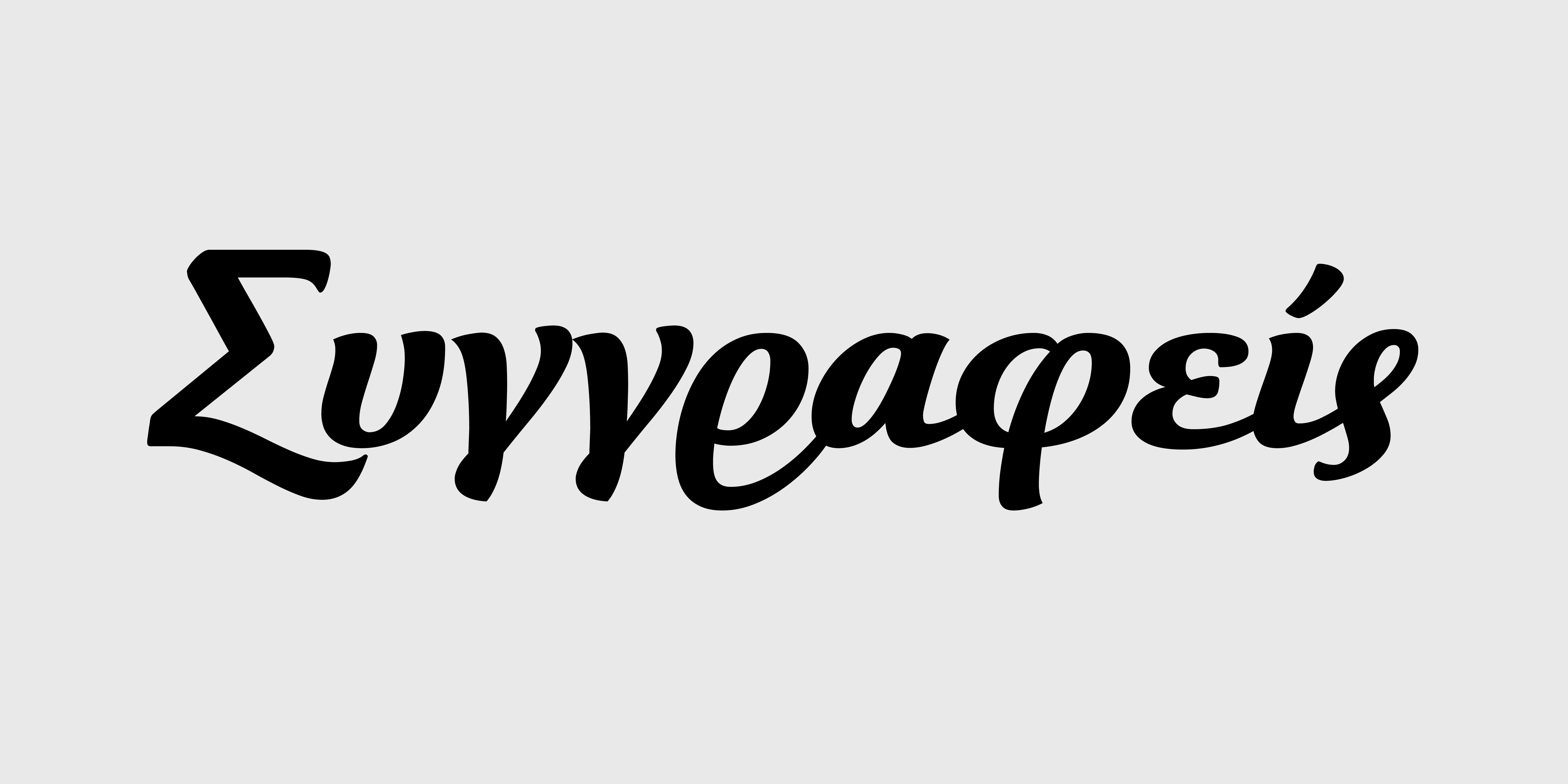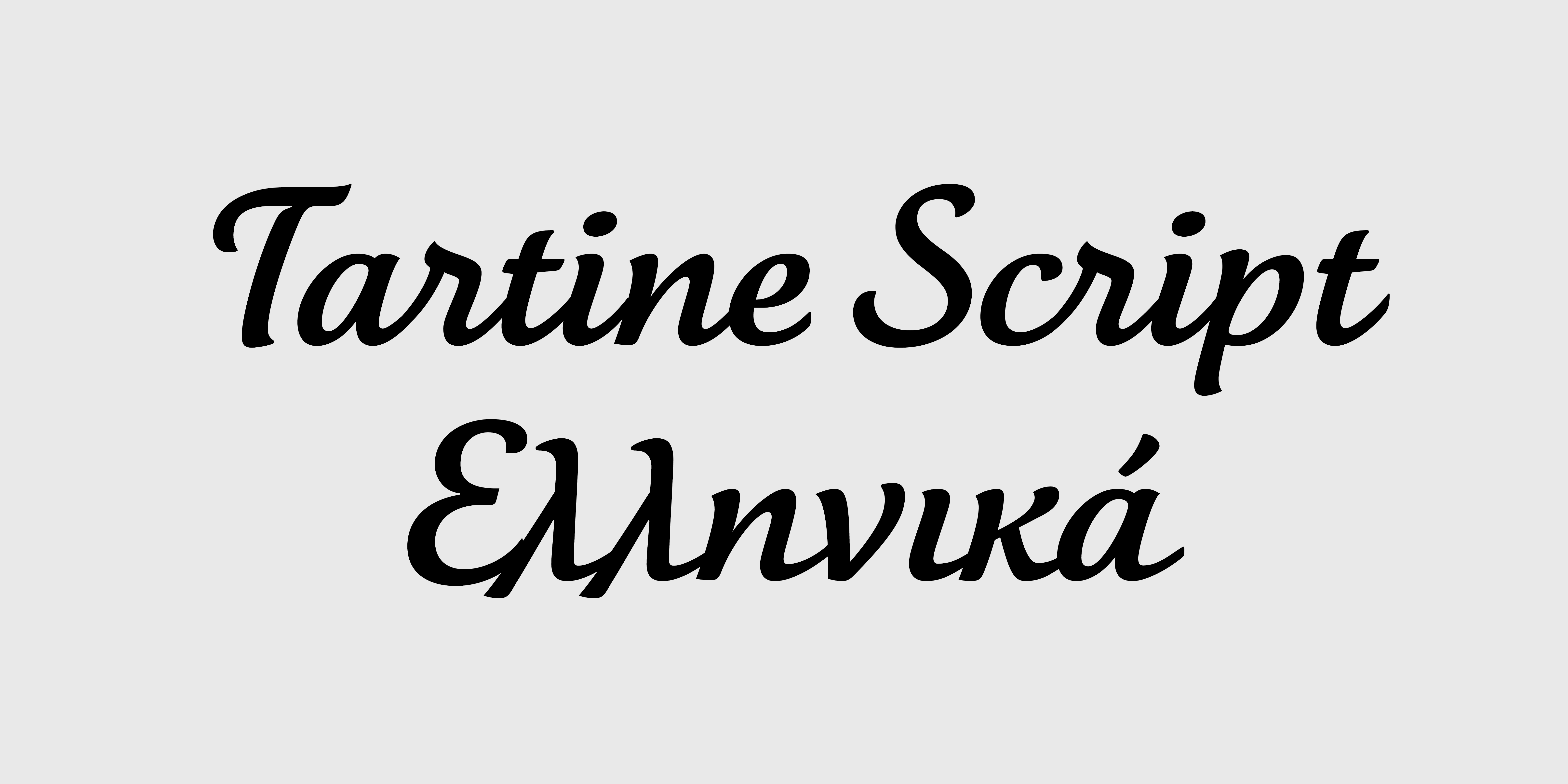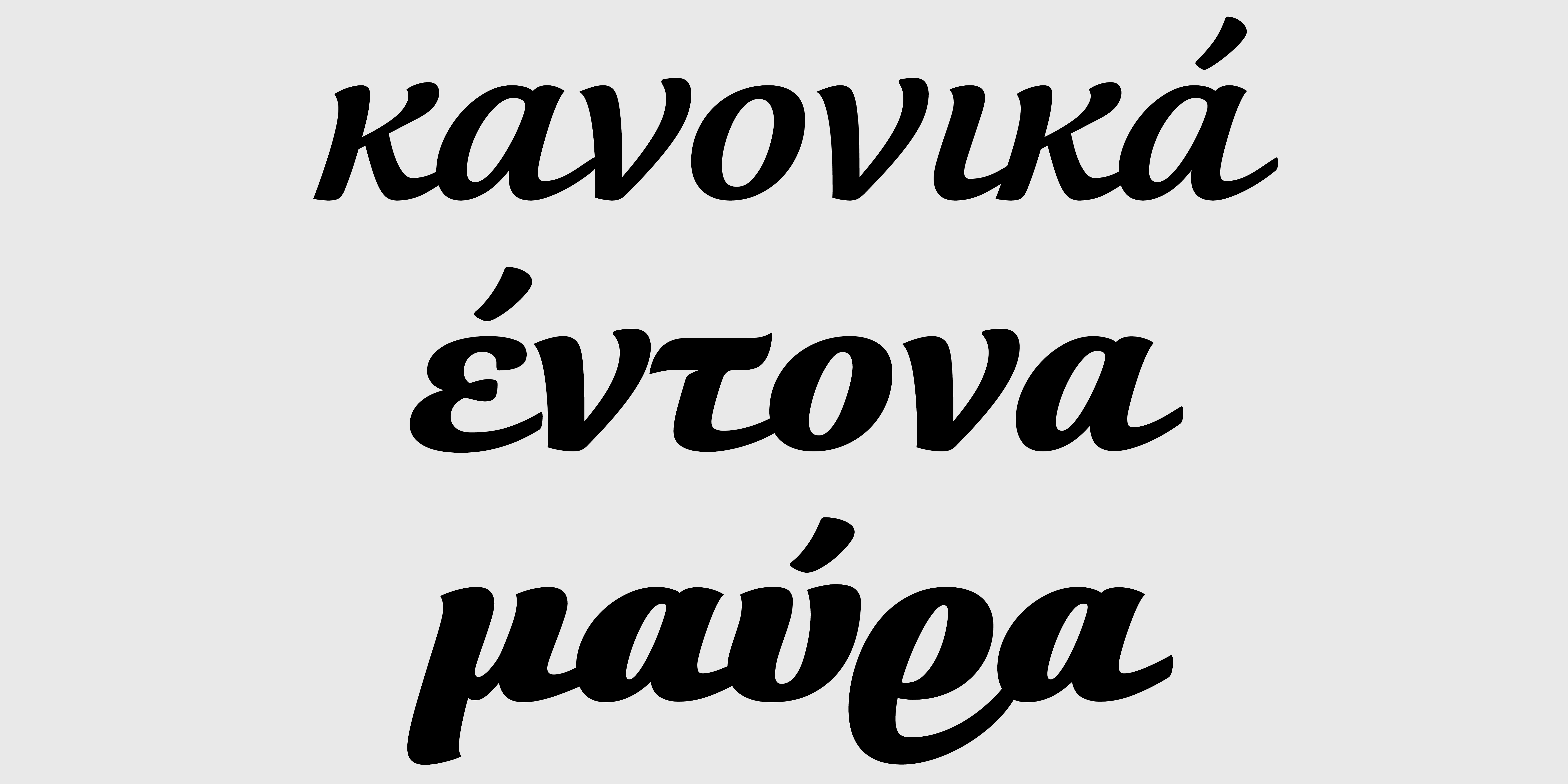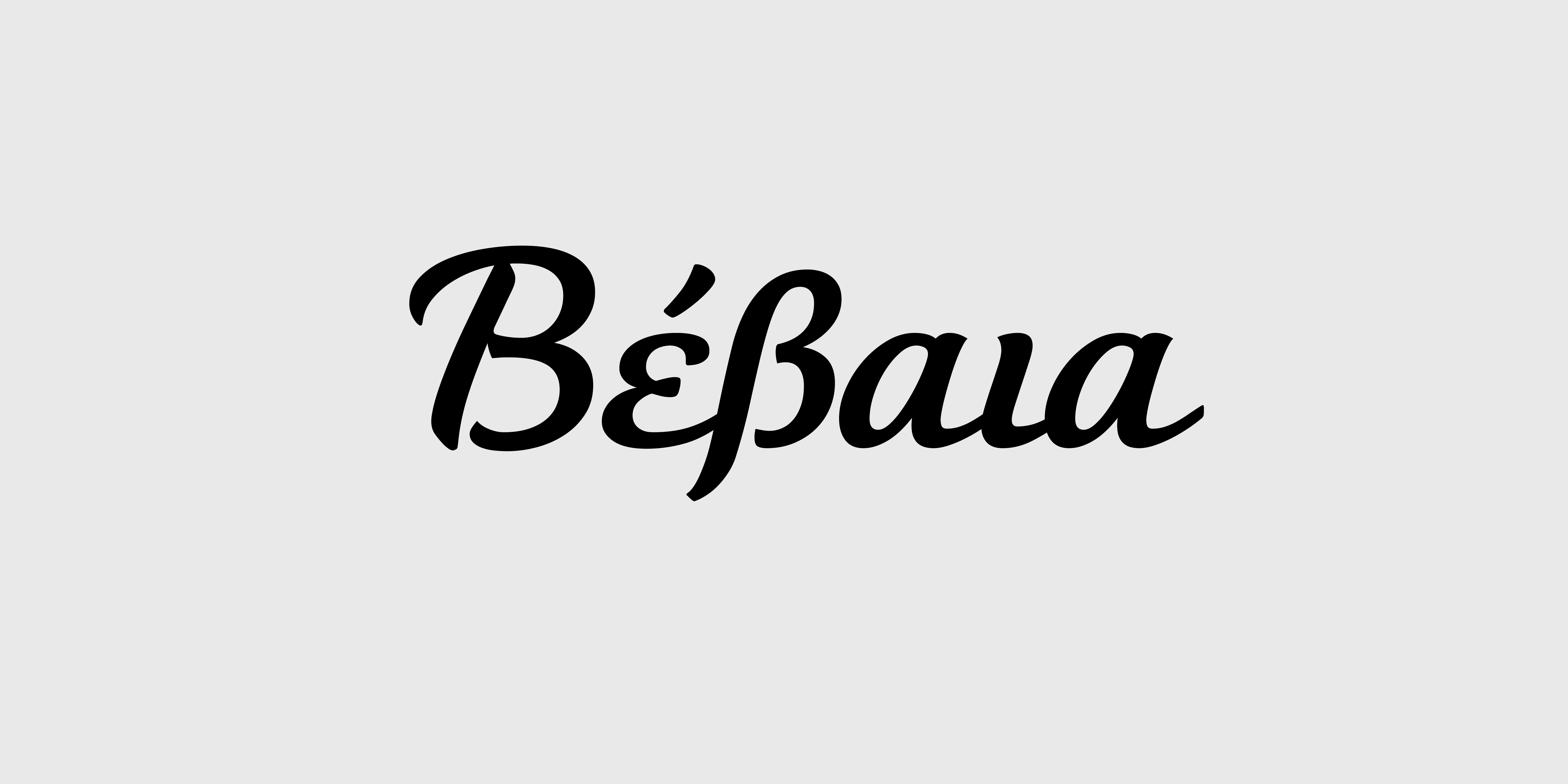
Tartine Script Pro
Σύμφωνα με το σχεδιαστή η γραμματοσειρά είναι ιδανική για χρήση σε συσκευασίες και ιδιαίτερα για supermarket. Όταν χρησιμοποιηθεί στο λογότυπο κάποιας κρέμας πουτίγκας ή αλλαντικού, τροφής για κατοικίδια μαλακτικού ή απορρυπαντικού, αποπνέει μία ζεστή και φιλική αίσθηση. Η TartineScript καλύπτει την ανάγκη στη χρήση μιας όμορφης και βαριάς χειρόγραφης γραμματοσειράς με την αίσθηση πινέλου που συμπεριφέρεται το ίδιο καλά προσθέτοντας στο ύφος είτε μιας πρόχειρης (casual) είτε μιας σοβαρής (formal) σύνθεσης.